Как подготовить шрифт для дореформенных текстов: Ѣ, Ѳ и І
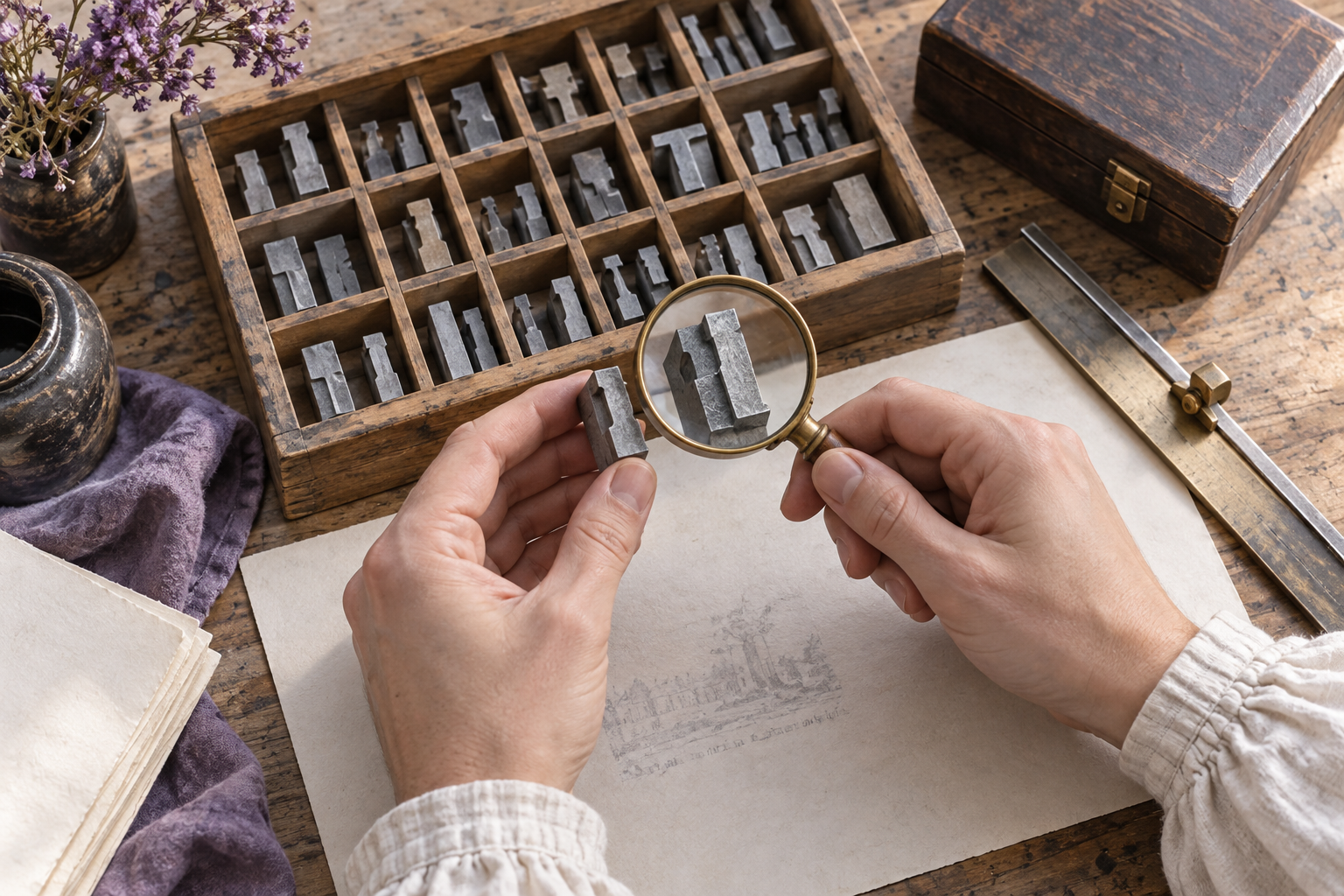
Дореформенный русский набор требует отдельных глифов для ятя Ѣ, фиты Ѳ и десятеричного і: замена их современными е, ф и и сохраняет приблизительное чтение, но стирает орфографию источника. Для шрифтового проекта важно не только нарисовать прописные и строчные формы, но и назначить правильные символы Unicode, проверить соседства и убедиться, что текст не подменяется латиницей или системным шрифтом.
Сначала определите, какой текст вы набираете
Состав набора зависит от редакционной задачи. Факсимильное воспроизведение старой страницы требует точной передачи исходной графики, включая особенности конкретного издания. Современная транскрипция может сохранять дореформенную орфографию, но использовать нынешнюю пунктуацию и наборные правила. А стилизация под старину часто оставляет современное написание и меняет только рисунок букв. Это три разных заказа; смешивать их на этапе проектирования шрифта неудобно.
Перед рисованием соберите короткий контрольный текст из источника, который действительно будете набирать. Зафиксируйте редакционный принцип: сохраняете историческое написание как в оригинале, нормализуете его или только имитируете визуальную эпоху. Если у вас нет готового текста, отметьте задачу как учебную пробу, а не как полную поддержку всех исторических вариантов. Тогда будет понятно, почему в набор включены именно эти знаки и какие случаи остаются за его пределами.
Не называйте Ѣ, Ѳ и І просто «буквами, удалёнными реформой» без оговорки о Ѵ. Исследование по истории реформы 1917–1918 годов указывает, что из графики были устранены ять, фита и десятеричное і, но ижица реформой не отменялась: к тому времени она употреблялась в немногих словах и постепенно выходила из употребления. Для контрольного набора Ѵ может понадобиться, если её содержит ваш источник, однако её историю следует описывать отдельно. См. статью «Реформа русской орфографии» в архиве «Тотального диктанта»: https://orfo.ruslang.ru/docs/articles/reforma_orfografii_1917.pdf.
Составьте карту символов до создания контуров
У каждого глифа должны быть две связи: имя внутри редактора шрифтов и кодовая позиция, по которой символ набирается. Для начального набора проверьте следующие пары: Ѣ/ѣ — U+0462/U+0463; Ѳ/ѳ — U+0472/U+0473; Ѵ/ѵ — U+0474/U+0475. У десятеричного і есть строчная U+0456; историческая прописная форма І обычно записывается кириллическим U+0406. Названия в Unicode могут описывать современные языковые применения тех же кодовых позиций, поэтому историческое назначение подтверждайте редакционной спецификацией, а не только именем символа.
Официальный перечень Unicode показывает пары ятя, фиты и ижицы в кириллическом блоке. Это полезная проверка кодовых точек и регистра, но не руководство по исторической орфографии: кодовая таблица отвечает на вопрос «какой это символ», а не на вопрос «в каком слове старого издания он должен стоять». Сверяйте карту кодов с выбранным источником и его транскрипционными правилами: https://unicode.org/Public/18.0.0/charts/nameslist/0400/.
Пара І и латинская I особенно легко смешивается при ручном наборе: очертания могут совпасть в отдельной гарнитуре, но символы принадлежат разным письменностям и имеют разные кодовые позиции. Не подменяйте кириллический знак латинским ради сходства рисунка. Вставьте в редактор отдельные примеры U+0406 и U+0049, затем копируйте текст в простой редактор и обратно: так вы проверите не только внешний вид, но и сохранение исходного символа.
Нарисуйте формы как часть той же гарнитуры
Начните с Ѣ и Ѳ, сравнив их с ближайшими современными знаками, но не стройте их механически из е и ф. Рисунок ятя в конкретном шрифте должен быть узнаваемым и согласованным по контрасту, засечкам, ширине и пропорциям. Фита тоже нуждается в собственной проверке: даже если она родственна ф по конструкции, она не должна случайно выглядеть как обычная ф с дефектом контура. Сначала определите опорные пропорции в прописной, затем проектируйте строчную пару.
Сопоставляйте новые буквы с системой, а не с абстрактным образцом из интернета. Поставьте рядом Е, Ф, И, прописные и строчные ять, фиту и і. Сравните высоту прописных, строчную высоту, толщину основных штрихов, форму засечек и ширину. Если гарнитура контрастная, тонкие элементы новых глифов должны поддерживать тот же ритм. В рукописном стиле сохраняйте характер движения пера, но избегайте случайного упрощения, которое делает два исторических знака похожими на современные.
Ижица требует отдельного дизайнерского решения: не назначайте ей форму греческой ипсилон или латинской Y только потому, что буква исторически связана с греческой. Ориентируйтесь на изображение в исходном издании и на стиль своего проекта. Если задача — не факсимиле, а согласованный авторский набор, сделайте форму визуально совместимой с кириллическим алфавитом и запишите в спецификации, какая редакционная форма выбрана. Источники различаются по эпохе и наборной традиции, поэтому образец из одного издания нельзя автоматически считать универсальным.
Для каждой прописной и строчной формы проверьте боковые поля и интервалы в контексте. Ять в сочетаниях с соседними округлыми или вертикальными буквами может выглядеть теснее, чем ожидается по одиночному глифу. Фита может создавать слишком плотную пару рядом с круглыми знаками. Проверяйте пары на привычном размере текста, корректируйте ширину и кернинг только после того, как глифы правильно связаны с символами.
Исторический кириллический набор начинается с редакционного решения: что именно вы сохраняете из источника. После этого зафиксируйте кодовые позиции, нарисуйте пары прописных и строчных в стиле гарнитуры и проверьте их в настоящем тексте после экспорта. Для собственного набора символов можно подготовить шаблон на Fontgenerator.ru, а затем отдельно сверить кодирование и состав итогового файла.